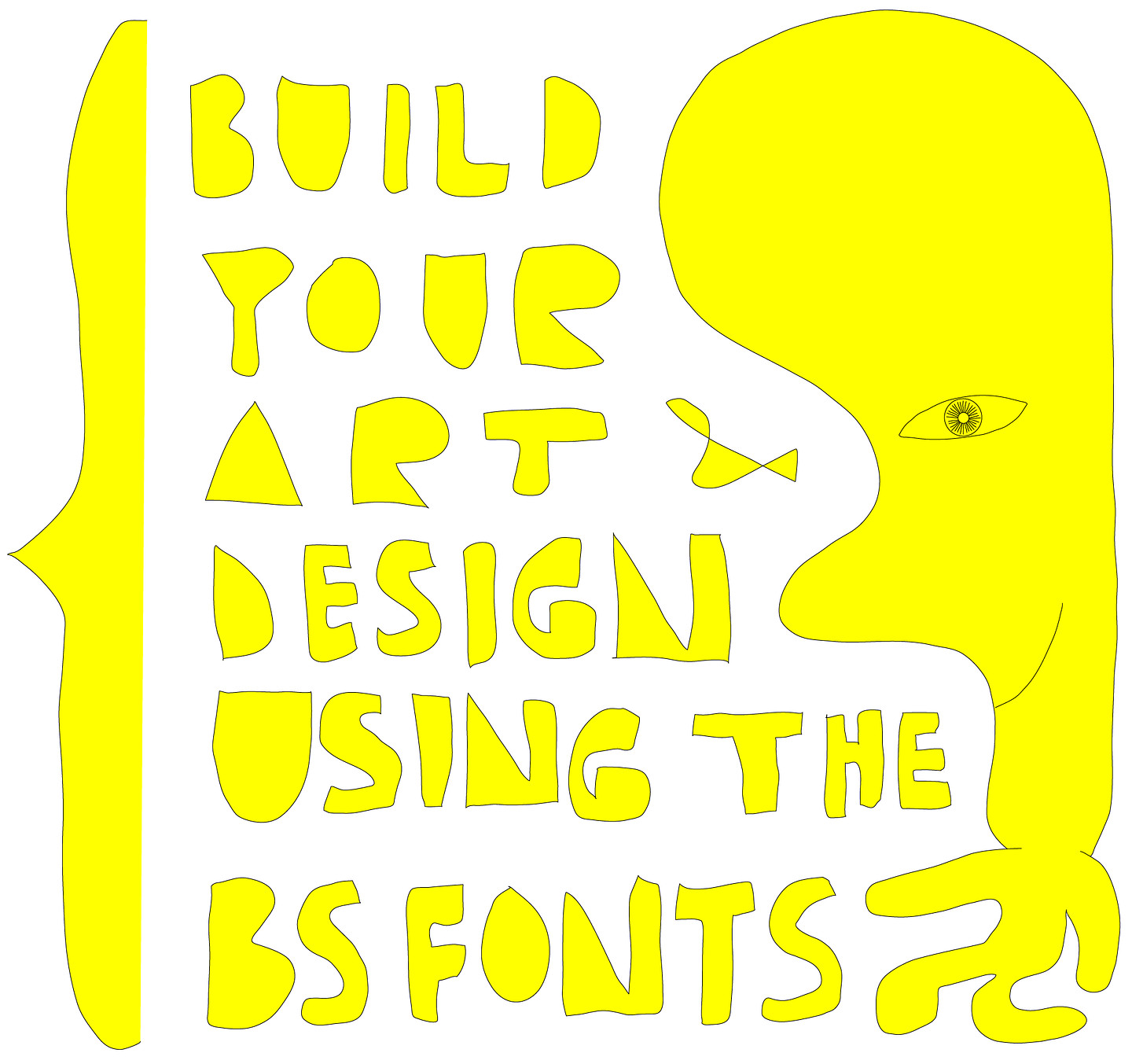
여러분이 세상에 없던 특별한 글을 썼다면, 그 제목을 디자인할 땐 붐스페이스BOOMSPACE가 만든 독특한 서체를 사용해 보세요! 안녕하세요? 재미있고, 변화무쌍한 서체를 디자인하는 붐스페이스BOOMSPACE입니다. 눈누에서 폰트로 만나게 돼서 반가워요! :)
서체 만드는 일은 재미있어요. 현대 한글에 라틴 글자까지 합치면 대략 12,000자 정도를